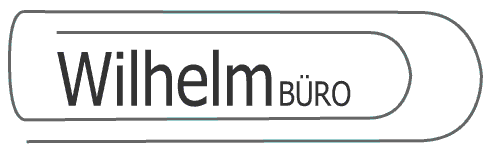
Schrift für Bürofirma, die billig und konservativ wirken wil
Habe wenig Ahnung von Design, wurde jedoch von einem Freund mit der Aufgabe betraut ein Logo für eine Bürofirma zu gestalten. Kann mir jemand sagen, ob die Tahoma den Wunsch treffen könnte, das Image einer konservativen und preisgünstigen Bürofirma zu repräsentieren?
Die Frage ist schwer zu beantworten. Ich bin der Überzeugung, dass eine Schrift einerseits zur Aufgabe passen muss, andererseits aber auch zum Auftraggeber. Ich nenne das »Maßschneidern«. Da keiner hier wohl deinen Kunden kennt und ein Gefühl dafür hat wer er ist, kann die Frage auch nicht wirklich jemand beantworten.
Die Tahoma ist eine herforragende Bildschirmschrift. Da spricht nichts dagegen. Ich würde sie aber nicht schmalverzerren (und ich trau mich was wetten, dass die Schrift in der Abbildung schmalverzerrt ist).
Naheliegend wäre für ein »konservatives« Bürounternehmen natürlich eine Schreibmaschinen-ähnliche Schrift. Ich würde mal die Andale Mono testen, die Letter Gothic oder – sofern vorhanden – die Officina.
Die erstgenannten machen es dann noch notwendig den Buchstabenabstand etwas auszugleichen. Das läuft zwar einer Monospace-Schrift entgegen, aber sonst sieht das irgendwie bescheiden aus.
Kliener Tipp: Ich würde die Dicke der Linien der Büroklammer deutlich verstärken. Vielleicht optisch an die stärkte der Linien der Buchstaben anpassen.
Ich hatte zuerst gelesen, daß es ein Logo für eine BAUfirma sein soll. Dann habe ich das Logo gesehen und gedacht: "Wenn schon Bau, dann eher Architekturbüro, aber eigentlich sieht´s aus wie Bürobedarf." Und siehe da: es soll ja für eine Bürofirma sein. Von daher stimmt die Anmutung des Logos. :-)
Die Idee mit der Büroklammer ist also schon nicht schlecht. Aber vielleicht solltest Du noch an der Umsetzung feilen. Alles in allem ist das Logo zu filigran, hat zu wenig Kraft. Schau Dir mal prägnante Logos an: Deutsche Bank, Die Bahn u. a. Kräftig, fast schon brutal. Aber erfolgreich.
Überlege auch, wozu das Logo gebraucht wird. Bei einem Schreibwarenladen ist es eigentlich nur als Ladenbeschriftung wirklich wichtig. Alles andere (Briefbogen, Visitenkarte...) ist wurscht, sieht eh´ kein Kunde. Und dem Lieferanten ist´s egal. Auch Anzeigen wird der Laden wahrscheinlich nicht schalten. Also konzentriere Dich auf die Beschriftung und mache ein Logo, welches am Laden gut aussieht. :-)
Du widersprichst Dir.
In der Überschrift Deines Beitrages schreibst Du "billig und konservativ".
Im Text schreibst Du "konservativ und preisgünstig".
Für "billig" brauchst Du etwas bewußt knalliges, für "preisgünstig", besser "preiswert" im wörtlichen Sinne "seinen Preis wert" dagegen etwas solides. (Beispiel aus der Zeitung: BILD und die ZEIT).
Deine Büroklammer-Idee assoziiert sicher jeder sofort mit "Bürobedarf". Das gefällt mir. Aber die Büroklammer ist falsch gezeichnet. Müßte an der spitzen Seite nicht rund sein, sondern abgewinkelt.
Den Schriftzug zur Büroklammer finde ich auch in Ordnung.
Es hat etwas solides, beständiges = konservatives.
Ah, ja.
Das ist jetzt natürlich sehr aufschlußreich.
Orangeowl, hat es bereits gut erklärt.
nur soviel: ich würde anstatt der tahoma die arial verwenden,
das gestauche hat sie nicht verdient, mit der arial kannst du
meinetwegen anstellen was du willst.
Entschuldige, ich hatte Deine hochgerollten Fußnägel als Reaktion auf meinen Kommentar verstanden. Bin nicht so vertraut mit dem Schreiben in Foren.
Das ist jetzt so als würde man sagen: Quäl doch anstatt der Katze lieber den Hund. ;-)
Ich möchte Miss aber auch kurz erklären, weshalb Schriften stauchen verpönt ist. Druck dir den Entwurf mal aus und häng Ihn an die Wand. Und dann wirf einen Blick auf die Rundungen beim h und beim m. Es ist deutlich zu sehen, dass sie verdickt sind, fetter als der Rest der Schrift. Ich glaube, das sollte auch ein ungeschultes Auge sehen. Weniger offensichtlich ist vielleicht, dass das W gerade im Verhältnis zum i zu mager – beinahe kränkelnd – wirkt. Ganz unschön ist der Auslauf des kleinen e unten. Das schwillt an seinem Ende noch einmal fett an.
Da ich eine richtige Büroklammer als Vorlage benutzt habe, weiß ich natürlich, dass meine Büroklammer nicht originalgetreu ist. Ich habe diese leicht verändert, um zwar noch die Assoziation zur Büroklammer zu erhalten, aber eben nicht nur eine Büroklammer abzubilden. Dank deinem Kommentar werde mir aber nochmal Gedanken über diese Entscheidung machen, da ich auch nicht möchte, dass man glaubt, der Gestalter wisse nicht wie eine Büroklammer aussieht.